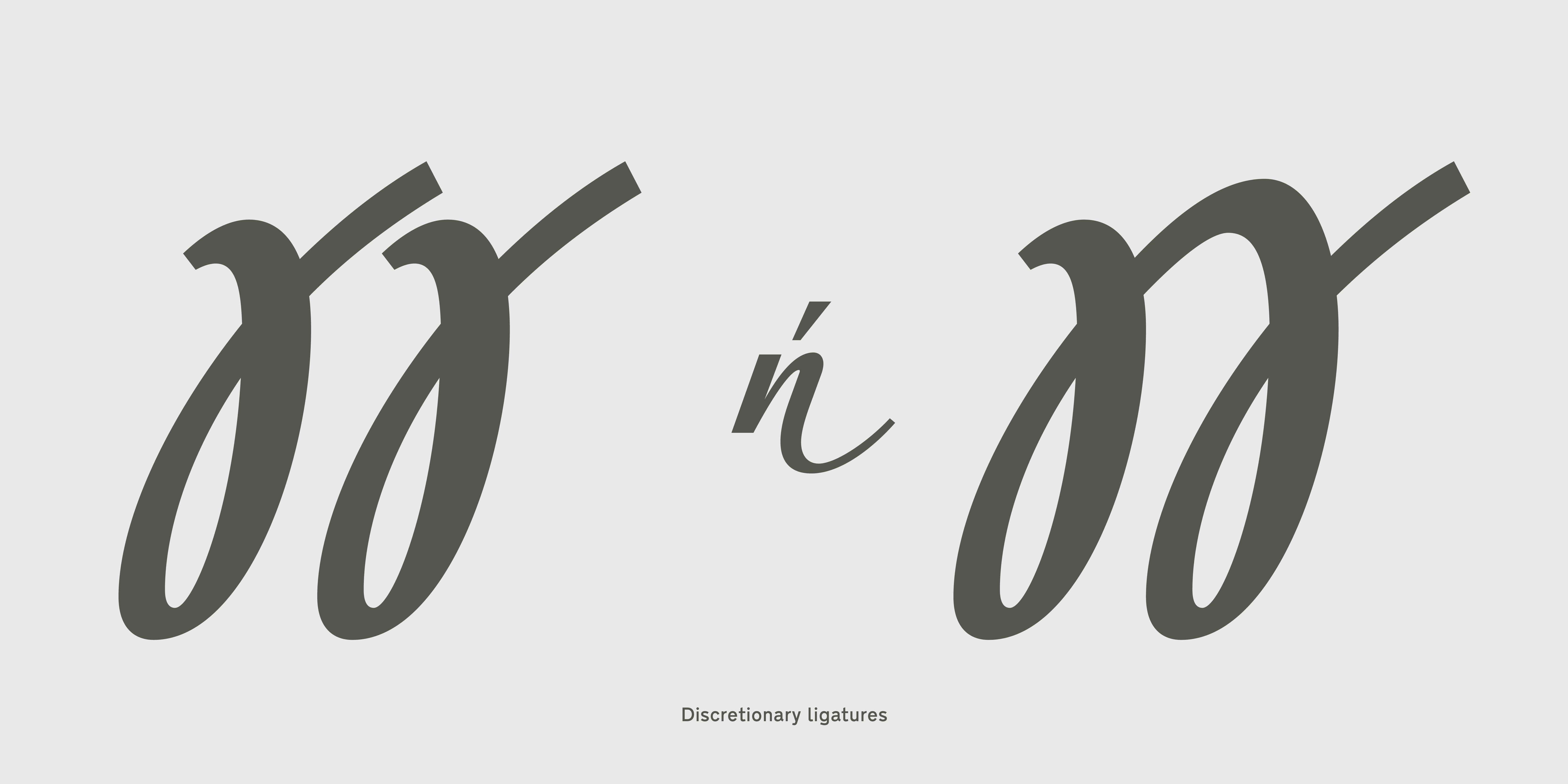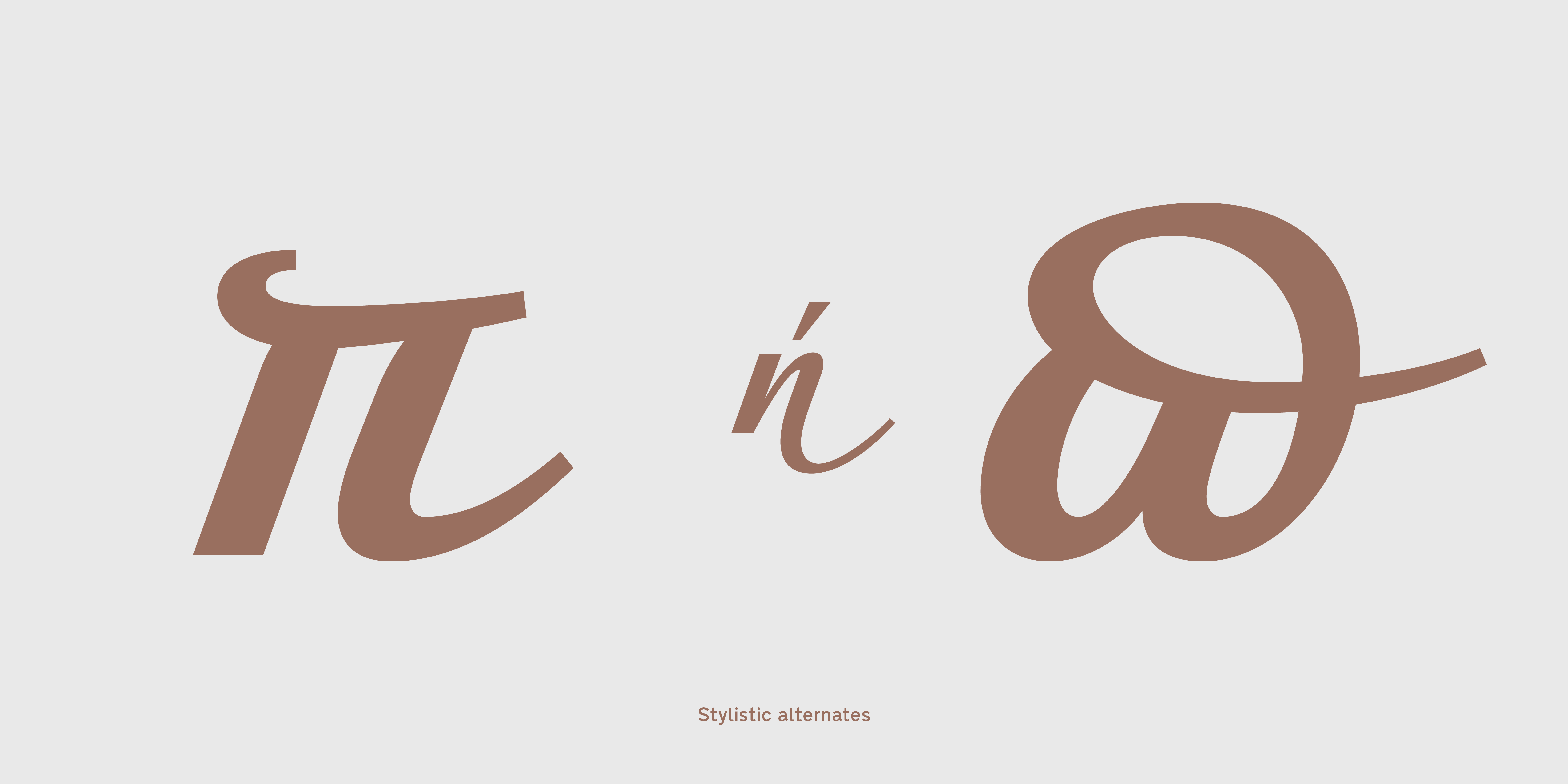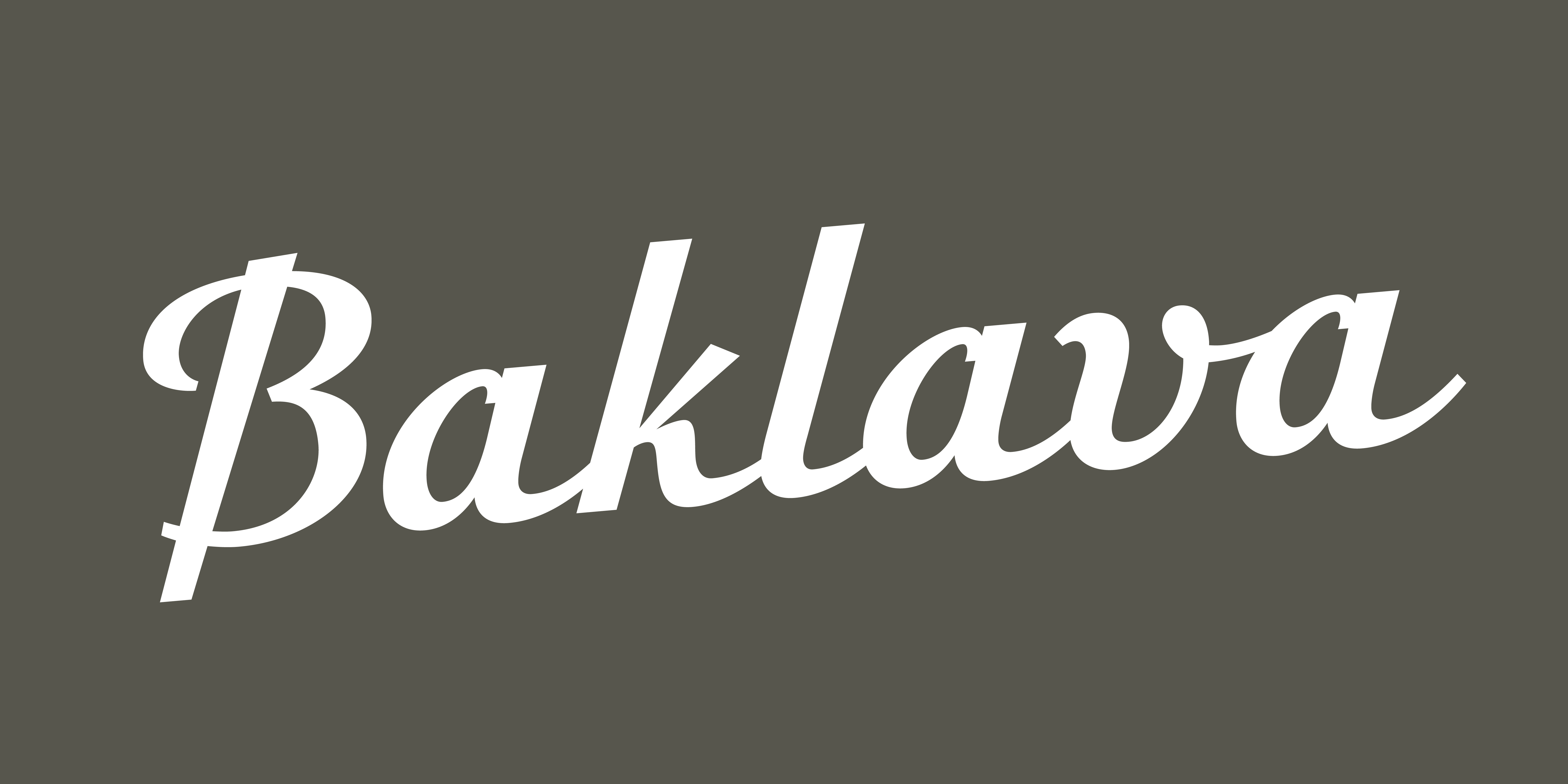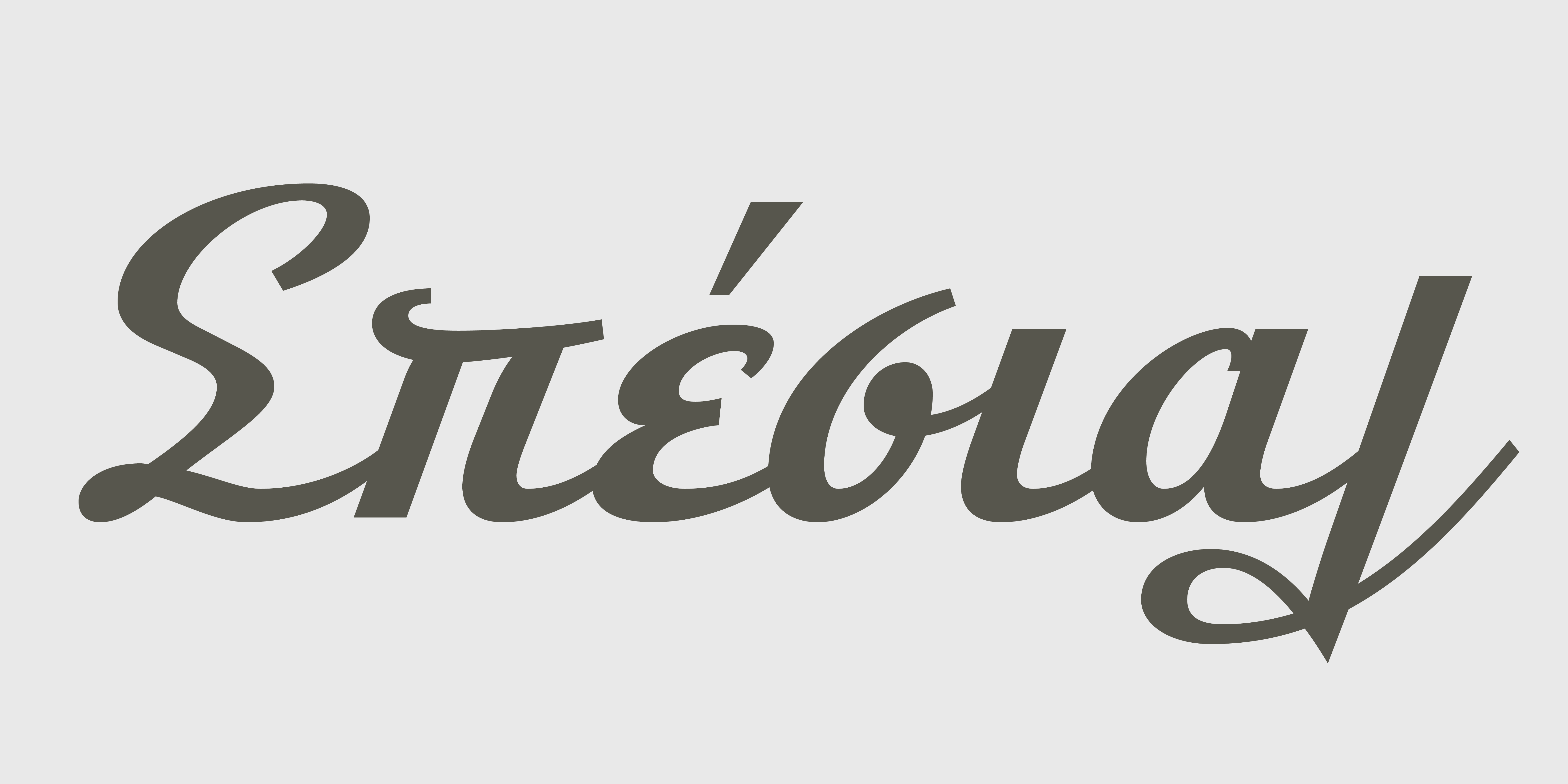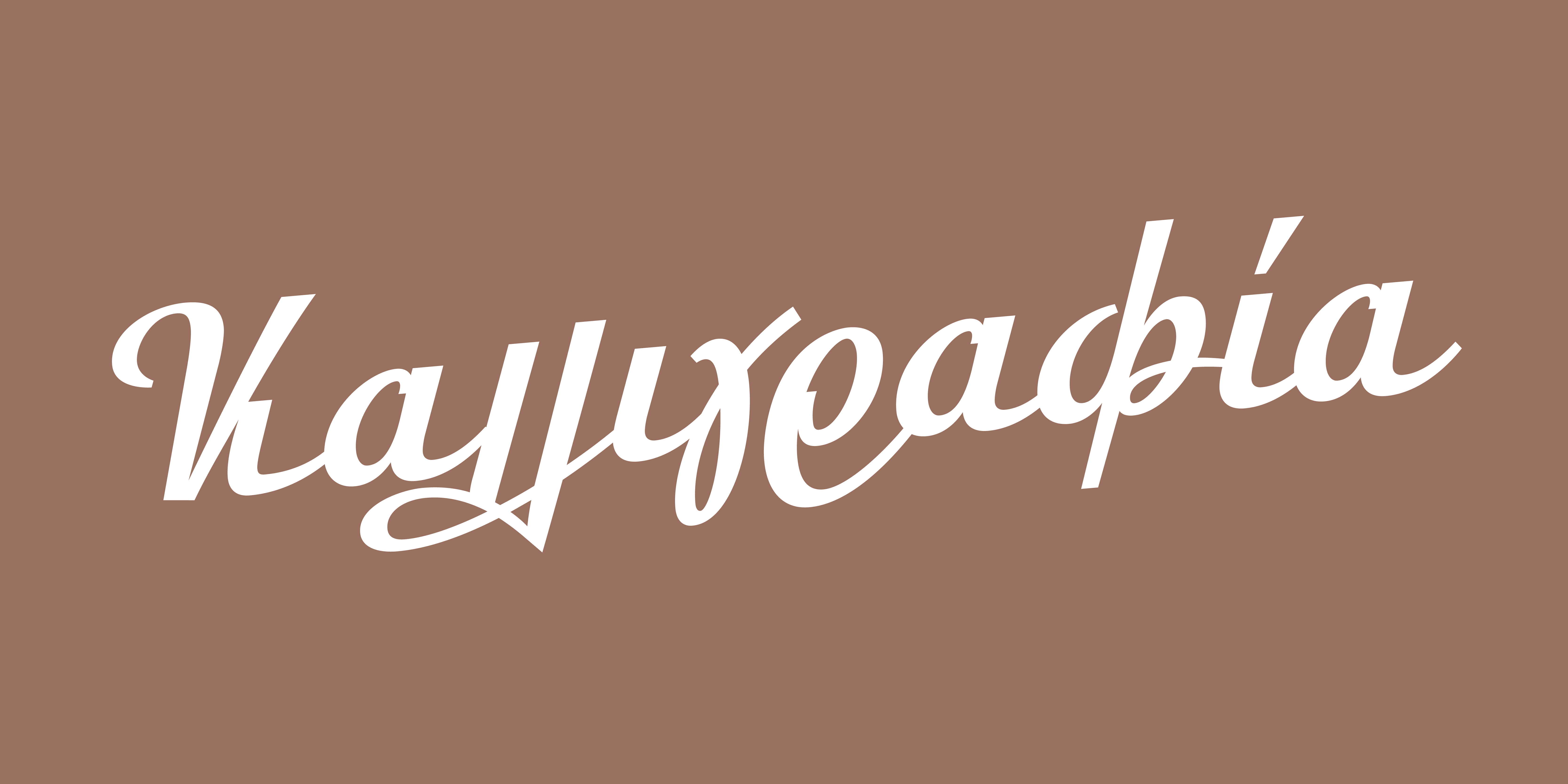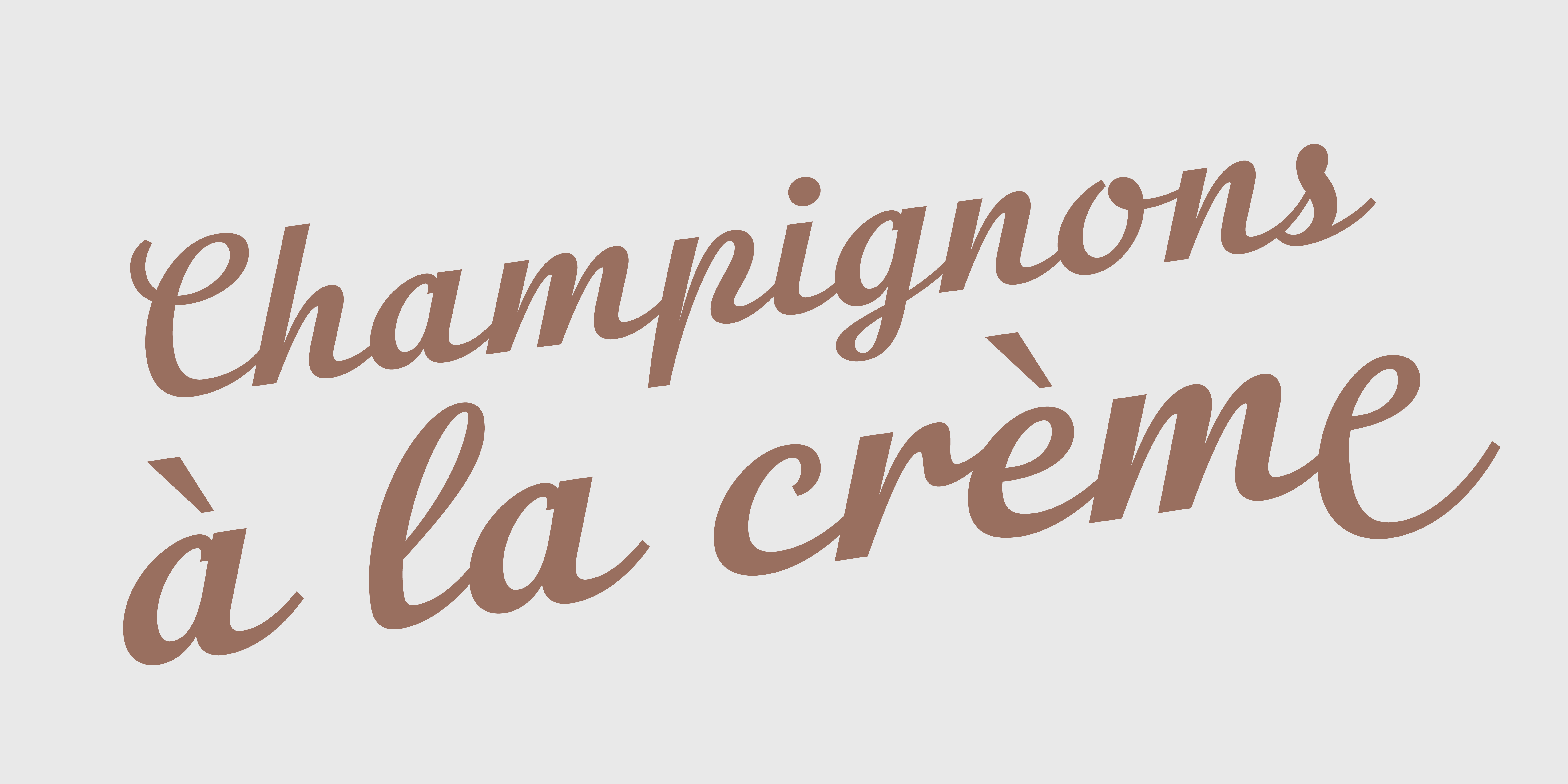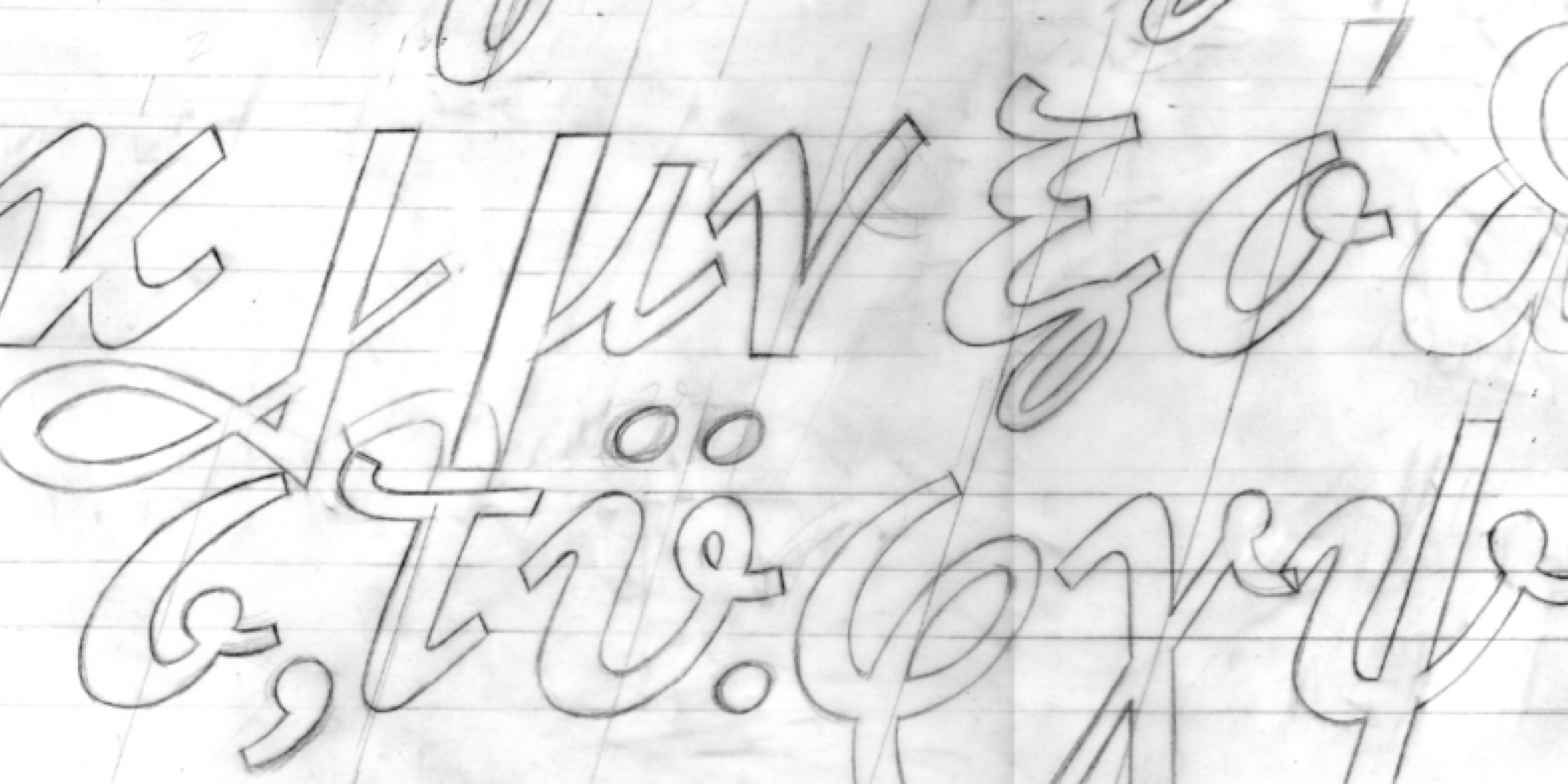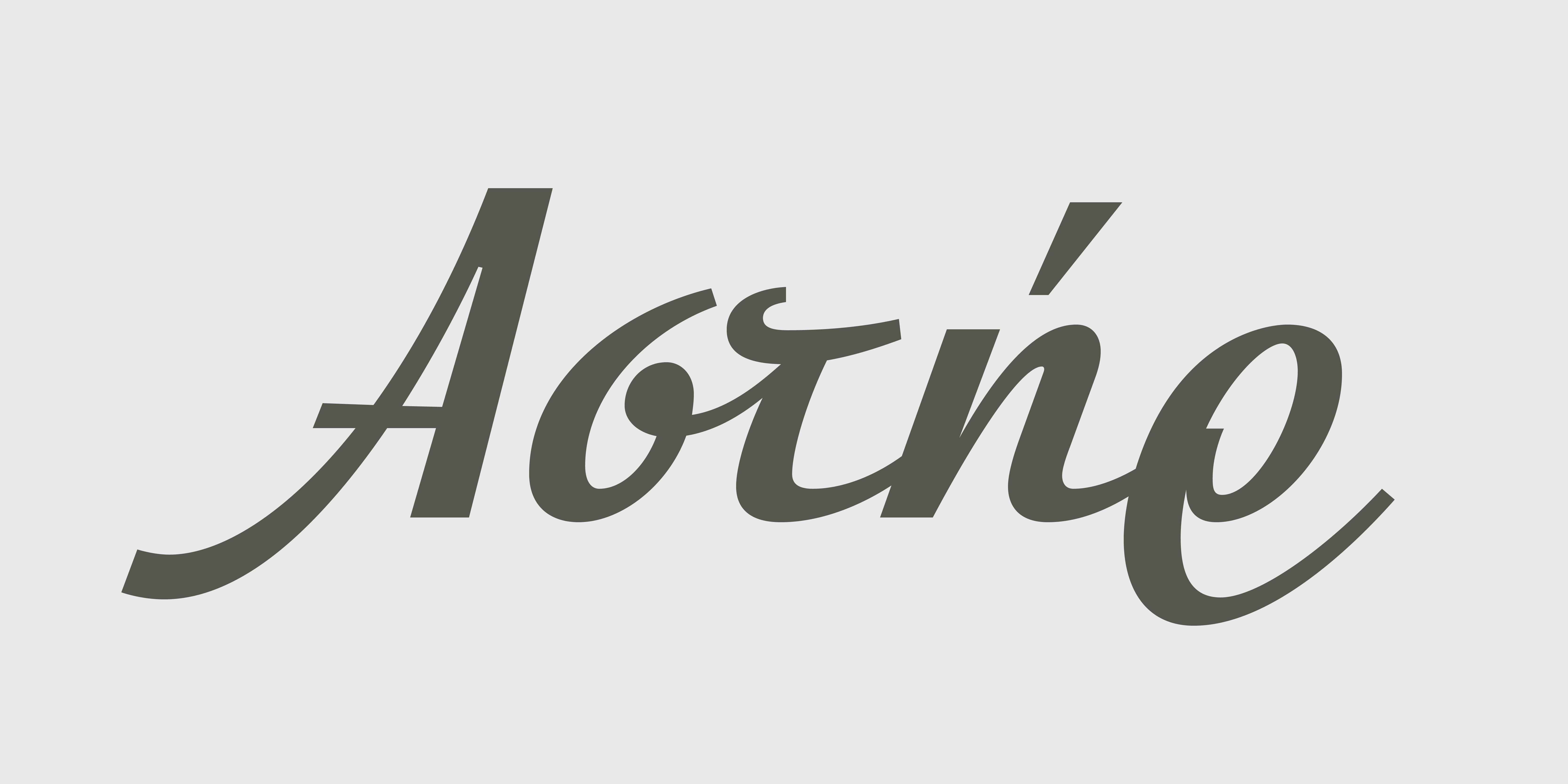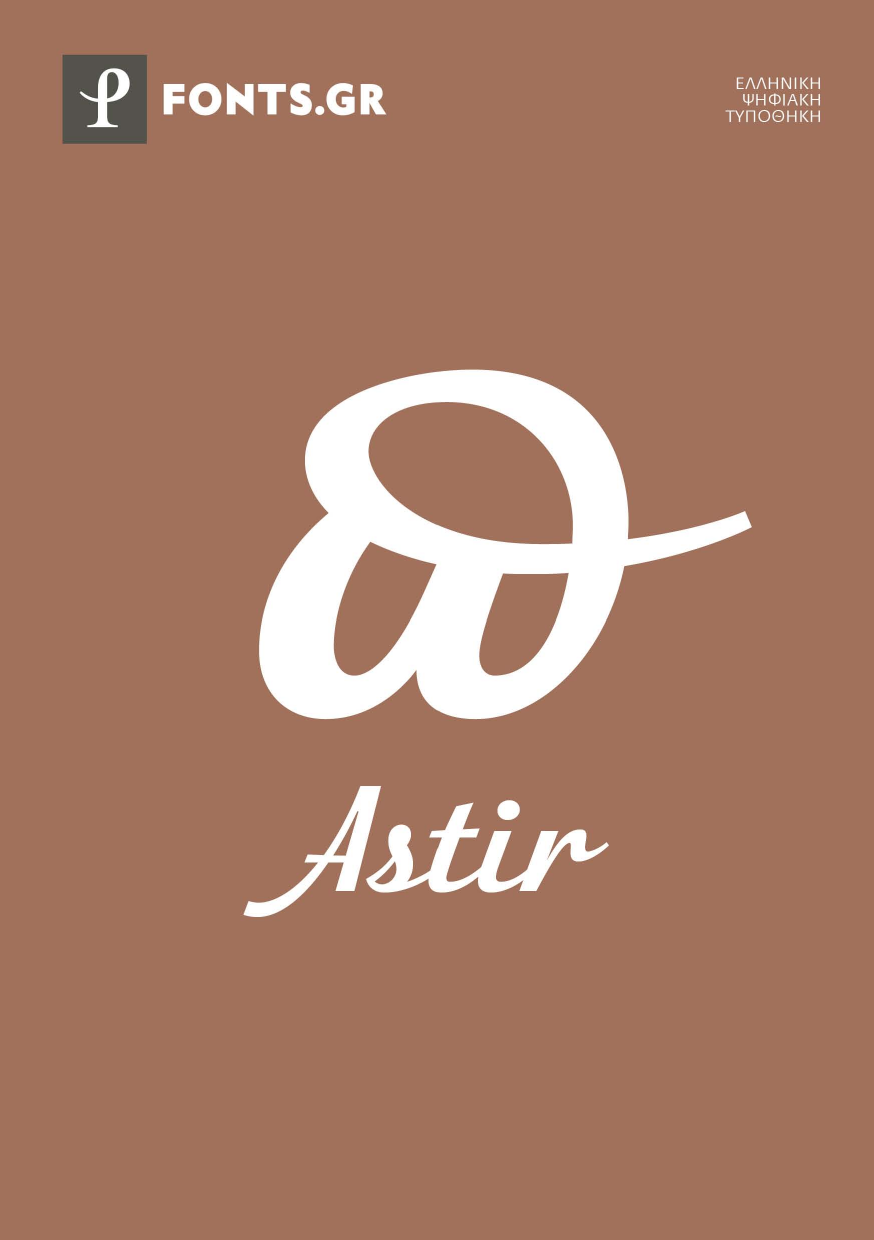
Astir
Η CF Astir είναι μια γραμματοσειρά σχεδιασμένη στα πρότυπα των ελληνικών καλλιγραφικών στοιχείων που χρησιμοποιήθηκαν ευρύτατα στην επιγραφοποιία και τη διαφήμιση μεταπολεμικά, μέχρι την δεκαετία του '70. Έντονα επικληνής, με αυξημένη αντίθεση πάχους κοντυλιάς και με συνεχόμενη γραφή, η CF Astir αποτελεί ένα παράδειγμα της εκφραστικότητας που χαρακτηρίζει την καλλιγραφία εκείνης της εποχής.